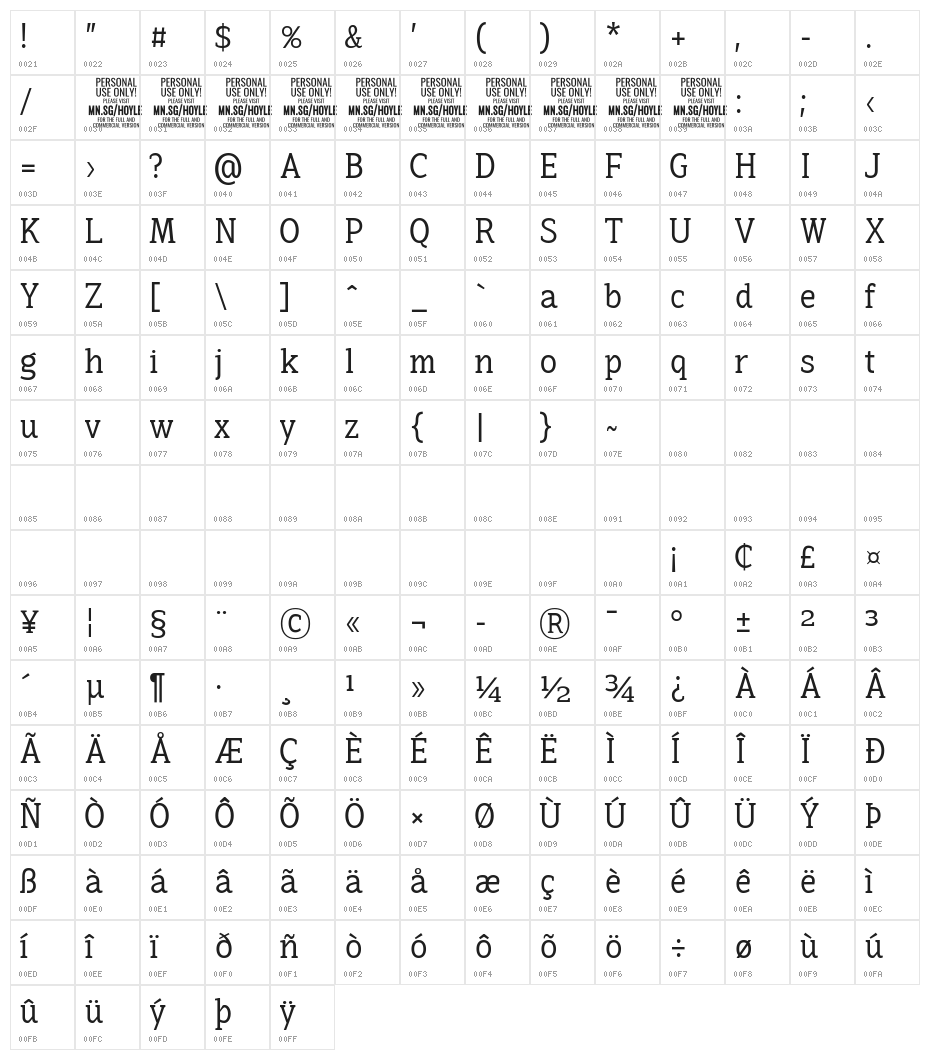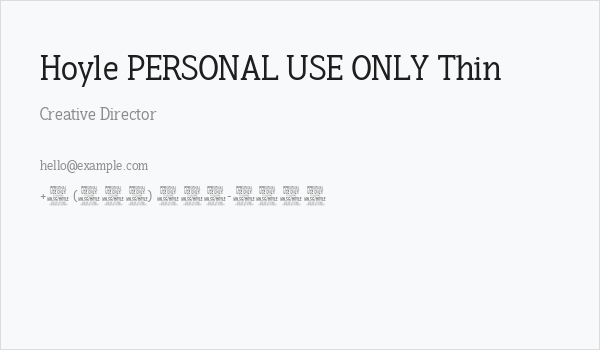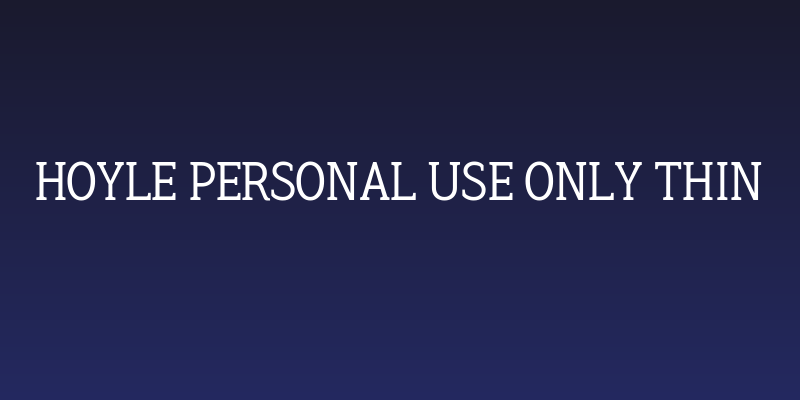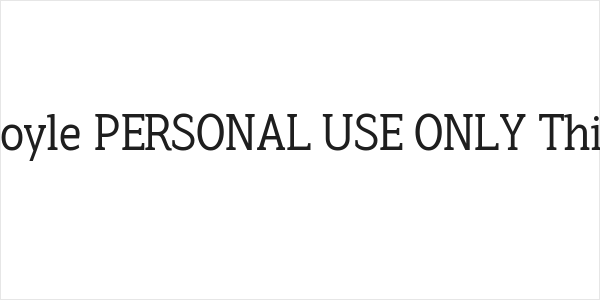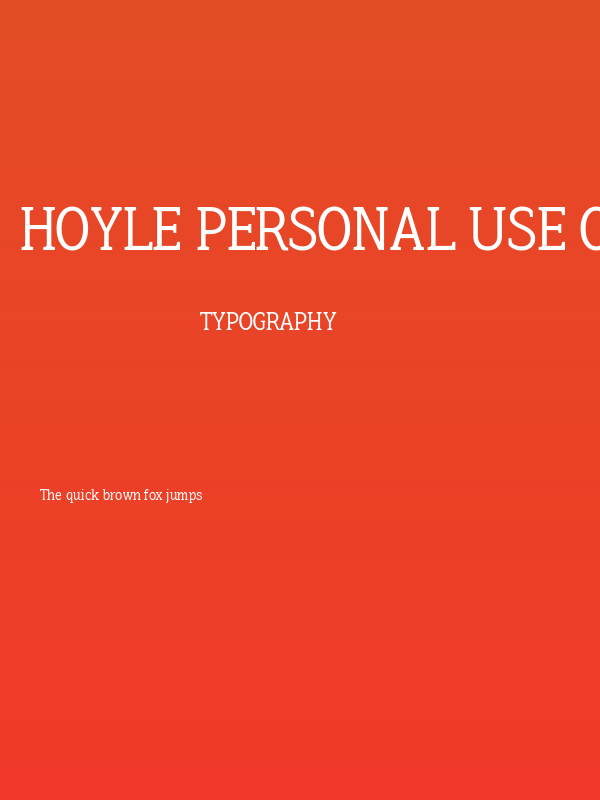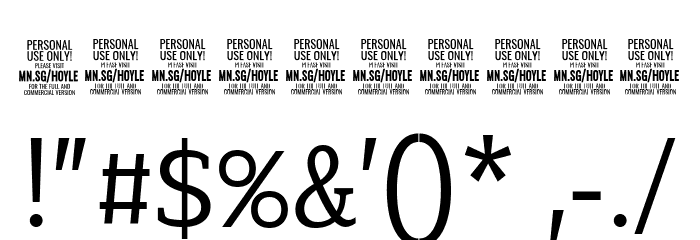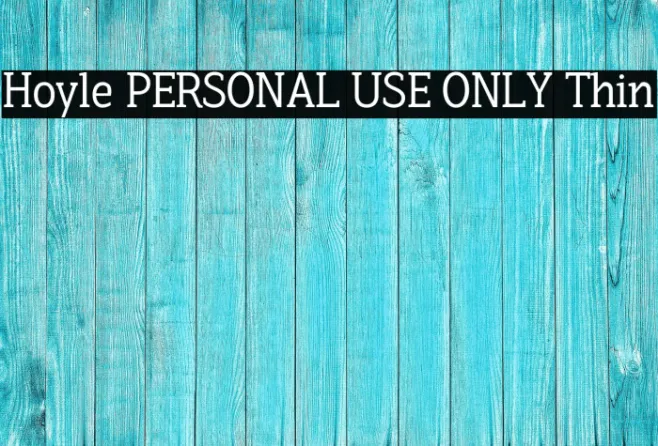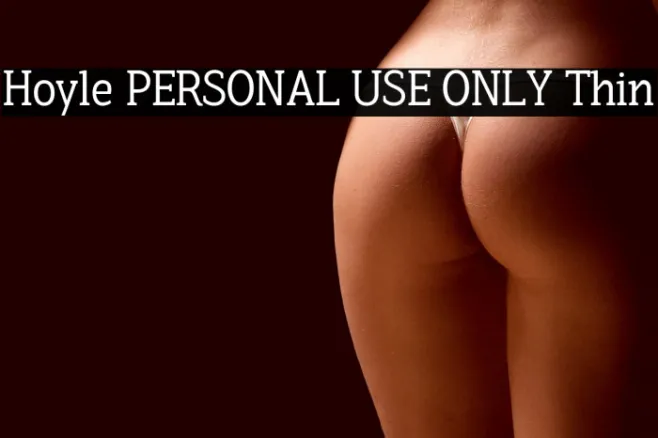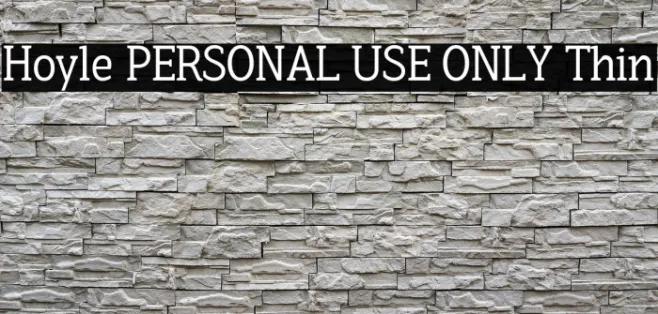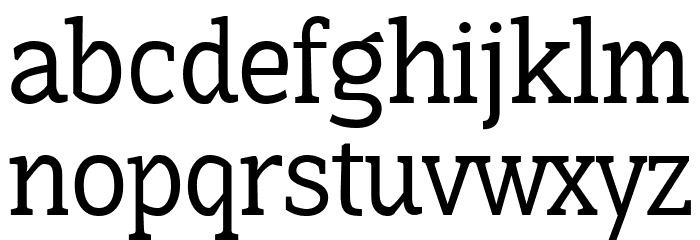
Hoyle PERSONAL USE ONLY Thin Font
| Estilo general | Classic |
| Caso de uso | Headlines, Body text, Logos |
| Proyectos propuestos | Ideal for editorial design, book covers, elegant invitations, and branding materials that require a touch of class. |